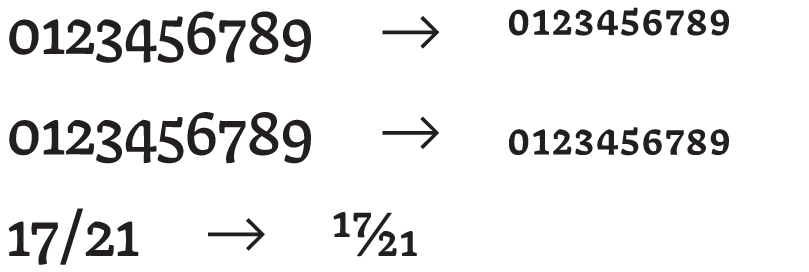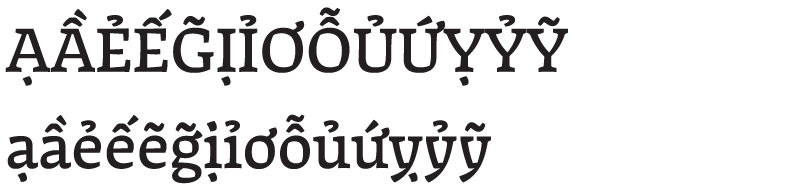
【対象フォント】
Vonk Pro Regular
Vonk Pro Italic
【Vonk Proのファミリー・文字セットの拡張とそれに伴う調整】
Vonk Proは2018年にRegular / Italicのファミリー構成でリリースされました。2022年にMedium, Bold, ExtraBold, HeavyとそれぞれのItalicをリリースして、ファミリーを拡張しています。また同時に文字セットを拡張することで、ベトナム語とグアラニ語にも対応しました。
上記のファミリー・文字セットの拡張に伴いRegularとItalicでもグリフの追加と一部デザインの調整を行いました。
以下で追加されたグリフとデザインの調整についてご説明します。
【グリフの追加】
以下のようなグリフが追加されています。
分子用の数字と分母用の数字グリフ
上:分子用の数字
中:分母用の数字
下:使用例
ベトナム語・グアラニ語対応用のグリフ
ベトナム語・グアラニ語対応用グリフ例
スモールキャップの "SS" グリフ
上:スモールキャップの"SS" グリフ
下:使用例
【字幅、カーニングの調整】
字幅やカーニングの調整が施されています。改訂前後で行長に影響を与えますので、ご使用時にはご注意ください。